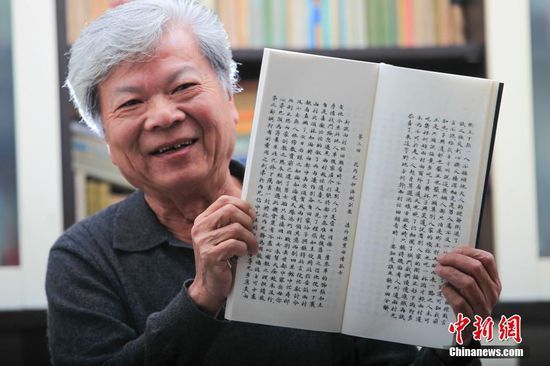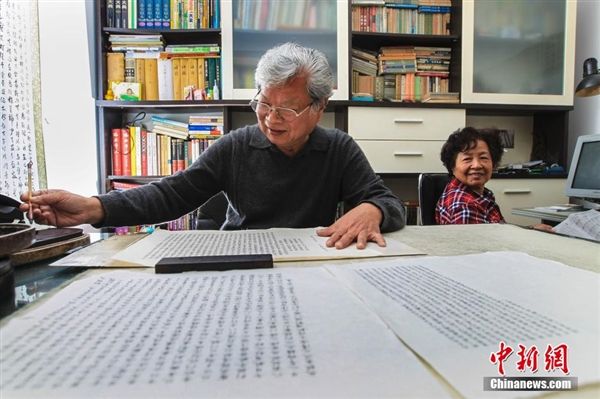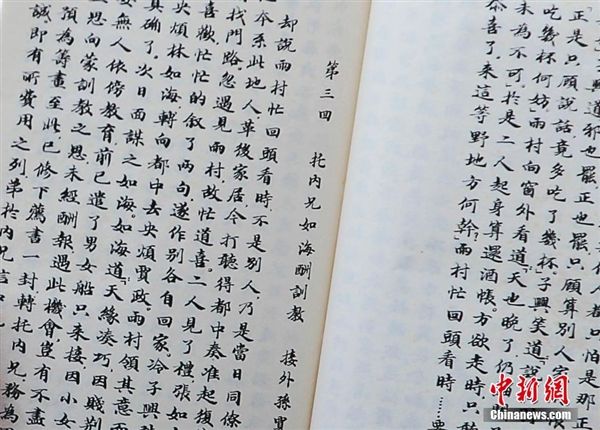
七旬老人小楷手抄《红楼梦》 工整字体惊呆网友
今年77岁的杨景方老人自幼就喜爱书法,多年来一直勤于练习,长期以来与他人的书信往来也是他们间的书法交流。退休后,闲暇的时间多了,搞书法创作成了他的日常活动内容之一,老人除了书法还喜欢阅读古典名著,对《红楼梦》更是爱不释手。5年时间,杨景方完成了小楷手抄长卷《红楼梦》。
4月19日,家住呼和浩特市五塔寺小区的杨景方老人向记者展示他的小楷手抄长卷《红楼梦》(如图),装裱好的书法长卷宽0.9米,总长392米的长卷被分装成3个卷轴,打开卷轴,只见洁白的宣纸上密密麻麻地写满了小楷,每个字只占约1平方厘米的地方,小楷字体既工整俊秀,又不失稳重大气。
七旬老人小楷手抄《红楼梦》:字体惊呆网友
《红楼梦》全书3卷120回,共计100多万字,动笔抄写之前,杨景方就精心挑选、备足了所需宣纸、墨汁及书写所用的小楷毛笔。用楷书抄写,字体本来小,加之书卷长,抄写时必须全神贯注,否则一个字错了,一张纸上的好几百字就又得重写,杨景方抄写时非常细心。为了督促自己坚持写下去,杨景方为自己规定了每天4个小时的书写任务。杨景方告诉记者,手抄《红楼梦》的5年来,光小楷毛笔他就用秃了400多支。功夫不负有心人,5年的坚持换来了完美的收尾,看着数百张宣纸上书写整齐,用笔讲究,散着墨香的小楷字体,杨景方和家里人喜不自胜,并请到装裱师傅精心装帧成轴。杨景方一直就有个心愿,就是可以将自己创作的长轴进行展示,与书法爱好者分享自己创作百万字小楷书法的经历,结果因为长轴太长找不到展示场所。费了很大的辛苦创作完成的长卷,却成了放在柜子里的藏品,只能在闲暇之余供家人和朋友看看,这让杨景方颇为遗憾。